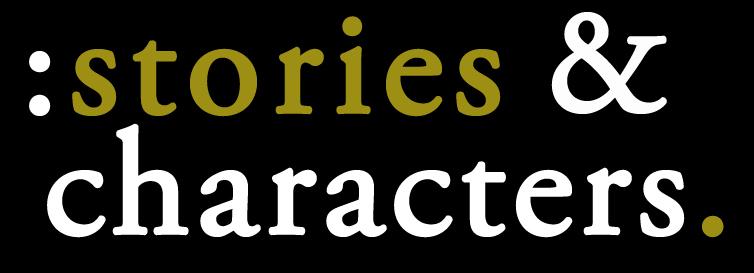
Suche Schrift dieses Blog-Logos von 2011 (stories & characters)
Ich suche den Font, der für das Logo dieses Blogs verwendet wurde. Es muß Anfang 2011 erstellt worden sein. Identyfont und Whatfontis tippen zuerst auf Adobe Garamond bzw. EB Garamond semibold. Das Logo sah für mich auf den ersten Blick auch danach aus, aber der verwendete Font ist weniger kantig – als hätte man Adobe Garamond etwas „rundgelutscht“, etwa zu sehen am Querstrich des t und am Schwänzchen des a.
Ich würede mal sagen, mit dem rundgelutscht hast du es schon getroffen: Um den Text, um ihn etwas fetter zu bekommen einfach ne Kontur mir abgerundeten Ecken in Schriftfarbe gelegt.